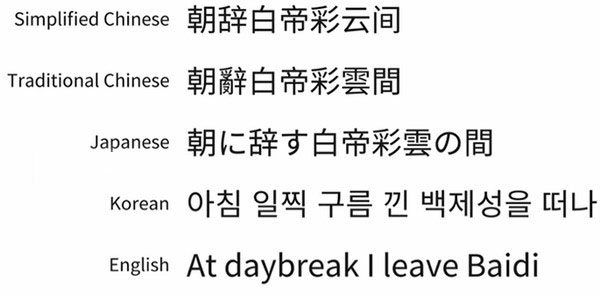
思源黑體是專為中日韓用戶開發(fā)的一款開源字體,由Google和Adobe共同開發(fā),Google將其命名為Noto SansCJK,Adobe則命名為Source Han Sans。思源黑體一共包括七種字體粗細(xì)((ExtraLight、Light、Normal、Regular、Medium、Bold 和 Heavy)),完全支持日文、韓文、繁體中文和簡體中文,還包括來自 Source Sans字體家族的拉丁文、希臘文和西里爾文字形共65536個(gè)字形。